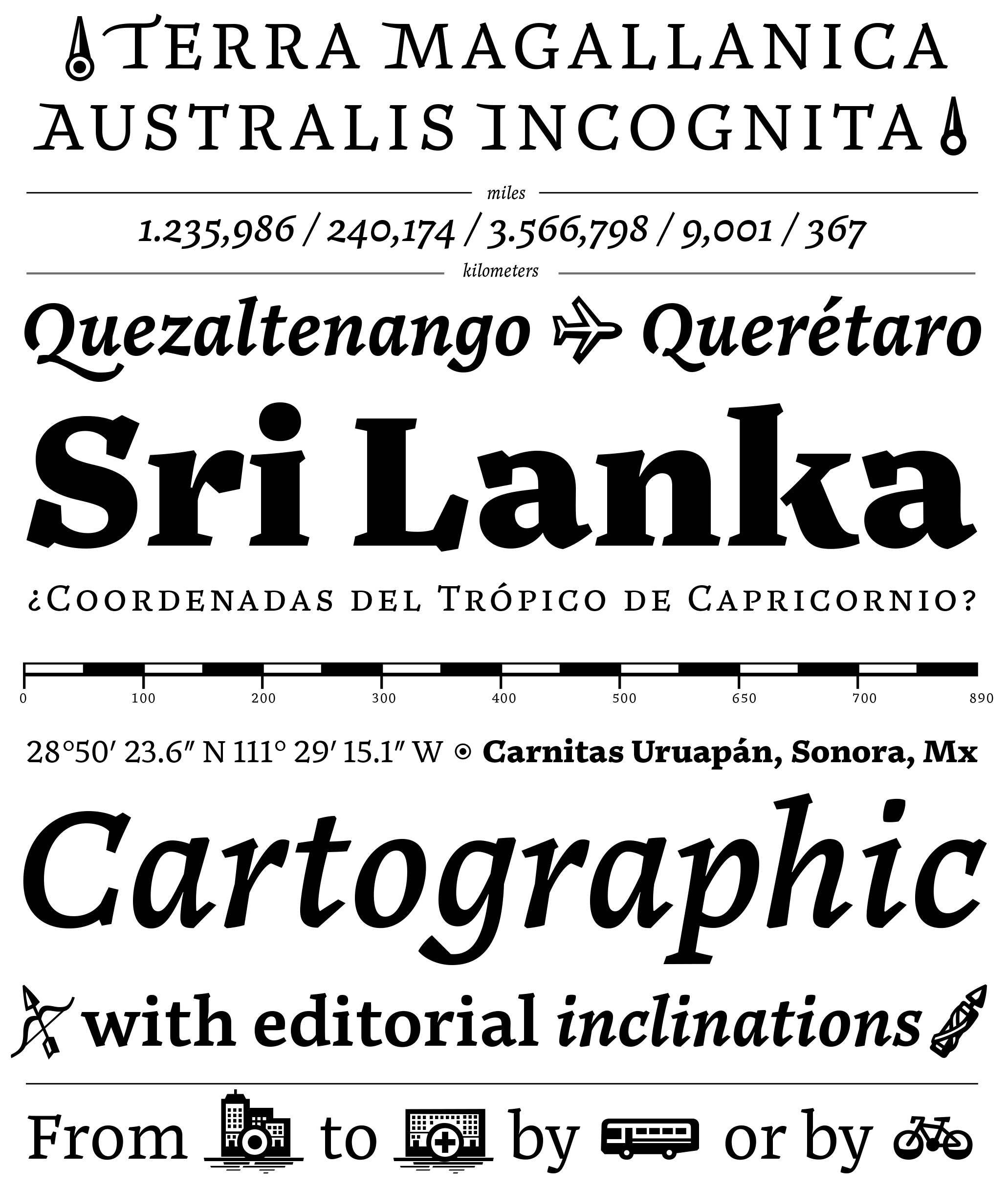
| Año | 2017 |
| Créditos | Juan Bruce |
| Descripción | La familia tipográfica Noort, diseñada por Juan Bruce, trasciende el ámbito del señalamiento y la cartografía para posicionarse como una herramienta integral en la organización de la información y en la generación de experiencias de lectura significativas. Su propósito fundamental coincide con el del diseñador de información: aportar claridad y estilo en contextos donde el volumen de datos puede resultar abrumador. La tipografía articula jerarquías visuales con solidez y adquiere mayor presencia mediante el uso del color en capas, consolidando una postura activa dentro del diseño editorial. |
| Clasificación | Texto |
| Familia(s) | Noort |
| Estilos | 12 |
| Set | Especializado |
| Fundidora | TypeTogether |